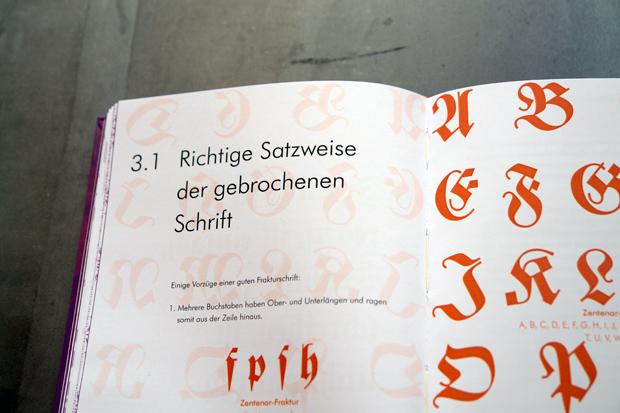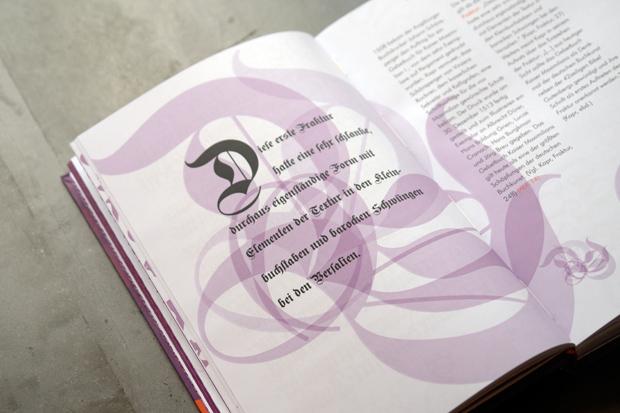
Die ursprünglich in Nordfrankreich entstandenen gotischen Lettern waren weit verbreitet; durch die Beliebtheit der »deutschen« Schrift während der Zeit des Nationalsozialismus wird die Fraktur seither nur noch selten verwendet – und oft auch in einschlägigem Kontext. Dieses Buch stellt ein Bemühen um die Rehabilitierung der Fraktur dar, indem es auf die Ästhetik dieser Schrift und die in ihr liegenden gestalterischen Möglichkeiten abzielt, jenseits von ideologischen Vorbehalten. Es führt in die Typografie der Fraktur ein, informiert über den jahrhundertelangen Streit zwischen Anhängern der runden und der gebrochenen Schriften und zeigt anhand von Grafiken und anderen Anwendungsbeispielen das grafisch reizvolle Potenzial dieser Schriftgattung. »Dear Ms Brauch, …« eröffnet eine Publikationsreihe, in der der Studiengang Informationsdesign der FH JOANNEUM hervorragende Abschlussarbeiten in jährlicher Erscheinungsform einer design-interessierten Öffentlichkeit präsentiert.
Rezension
Beim vorliegenden Buch handelt es sich um eine Bachelor-Arbeit im Studiengang »Informationsdesign« an der Fachhochschule Graz. Die Autorin verfolgt das Ziel, die Fraktur zu rehabilitieren, indem sie die Ästhetik und die in ihr liegenden gestalterischen Möglichkeiten aufzeigt, über die Geschichte der gebrochenen Schriften aufklärt und so Vorurteile gegen sie ausräumt.
Schlägt man das Buch auf, fühlt man sich unweigerlich an Judith Schalanskys »Fraktur Mon Amour« erinnert. Beide Autorinnen wollen die gebrochenen Schriften durch eine zeitgemäße Gestaltung von ihren bekannten assoziativen Altlasten befreien. Auch das Buch von Elisabeth Gruber setzt daher auf kräftige Farben und einen großflächigen ornamentalen Einsatz von Frakturbuchstaben. »Dear Ms Brauch« präsentiert allerdings keine Schriften, sondern will seinem Anspruch nach ein Lesebuch sein, auch wenn die verspielte Gestaltung der Lesbarkeit zuweilen etwas abträglich ist.
Nach einer kurzen Definition, was der Ausdruck Fraktur überhaupt bedeutet, wird ausführlich erklärt, wie die verschiedenen gebrochenen Schriftarten historisch entstanden sind. Der nächste Abschnitt beschreibt am Beispiel einzelner Schriften, wie sich im Laufe der Zeit die Form der Fraktur geändert hat. Anschließend werden Vorteile der Fraktur gegenüber der Antiqua aufgezählt. Die Regeln zum richtigen Einsatz des langen und runden s sowie der Ligaturen werden leider nur unvollständig erklärt. Im Anschluss daran wird ausführlich über die Zweischriftigkeit im deutschen Sprachraum, den Schriftstreit von Fraktur- und Antiqua-Anhängern im 19. und 20. Jahrhundert, die Rolle der Fraktur im Nationalsozialismus und das Frakturverbot von 1941 berichtet. Als Beispiele für die Anwendung der Fraktur im Dritten Reich sind Plakate und Zeitungen abgebildet.
Der anschließende Abschnitt behandelt die Verwendung gebrochener Schriften nach dem zweiten Weltkrieg in der BRD und DDR und im heutigen Alltag. Glanzpunkte der Fraktur, die nach 1945 vor allem in der DDR entstanden, zeigt sie jedoch wenige auf. Viele Bilder zeigen, wo heute noch Fraktur verwendet wird. Zudem hat Elisabeth Gruber Bilder von verschiedenen Produkten retuschiert und Antiqua-Beschriftungen durch Fraktur ersetzt sowie umgekehrt Fraktur-Beschriftungen durch Antiqua. Die geänderten Bilder sind den ursprünglichen Fassungen gegenübergestellt, so dass man sieht, wie man nur durch einen Wechsel der Schriftart einen ganz anderen Eindruck hervorrufen kann.
Fazit: Hält man sich vor Augen, dass dieses Buch eine Bachelor-Arbeit ist, so kann das Ergebnis in Inhalt und Umfang sicherlich überzeugen. Das Buch bieten einen lockeren und optisch ansprechenden Einstieg in die Geschichte und Gegenwart der gebrochenen Schriften. Dem gesteckten Ziel – durch die Aufklärung über die Fraktur eine Rehabilitierung zu erreichen und dieser Schriftgattung neuen Raum für eine heutige Anwendung einzuräumen – wird das Buch sicherlich gerecht.
Jedoch ist das Niveau einer Hochschularbeit nicht automatisch auch ausreichend um direkt verlegt zu werden. Hier hätte dem Buch ein fachliches Lektorat doch sehr gut getan. Denn als Student bedient man sich mangels eines tief greifenden Wissens des Themas natürlich vor allem dessen, was man in anderen Büchern findet und es werden nicht selten fragwürdige Aussagen unreflektiert übernommen oder missverständlich wiedergegeben.
Schon im Vorwort stutzt der fachkundige Leser zum Beispiel über die Aussage, die Fließtext-Schrift des Buches sei die 1928 von Paul Renner geschaffene Bitstream Futura Light – eine der Lieblingsschriften Hitlers*. (Bitstream wurde jedoch erst 1981 gegründet.)
Und auch die historische Auseinandersetzung mit der Rolle der Fraktur im 3. Reich und den »Schaftstiefelgrotesken« ist natürlich eine inhaltlich Tretmine, die umfassendes typografisches und gesellschaftspolitisches Wissen zu dieser Zeit erfordert, um hier eine nutzbringende Einschätzung geben zu können, die nicht nur die Ansichten aus anderen Büchern übernimmt.
Auch der Umgang mit dem Urheberrecht der verwendeten Materialien lässt Raum für Kritik. Die gezeigten Abbildungen wurden einfach aus anderen aktuellen Büchern gescannt oder aus dem Internet – zum Beispiel aus der Flickr-Gruppe Blackletter today – entnommen, ohne das Einverständnis der Urheber einzuholen. Auch dies ist im Rahmen einen internen Hochschularbeit vielleicht verzeihlich, hätte aber vor dem Verlegen des Buches korrigiert werden müssen.
* Nachprüfbare Quellen sind nicht bekannt. Die Autorin beruft sich auf Judith Schalansky